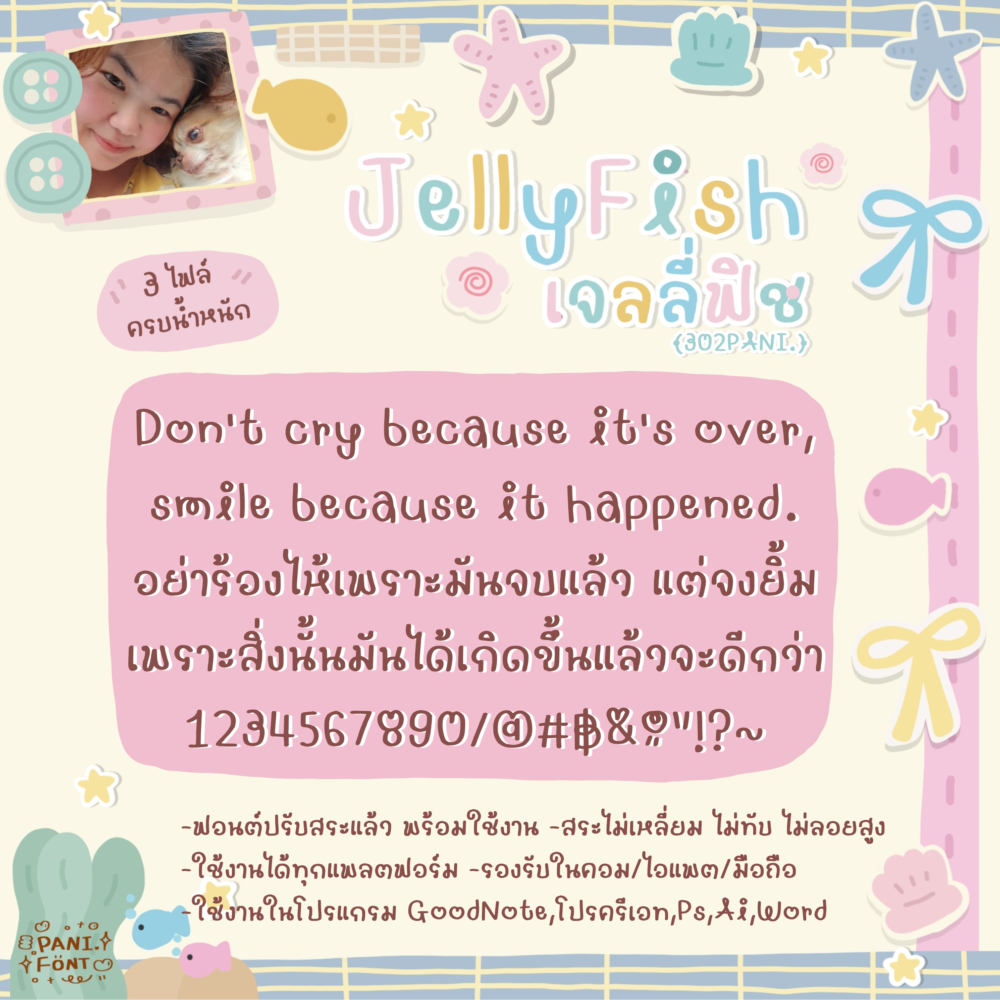
ฟอนต์แมงกะพรุน
นานๆจะเขียนแนวแฟนซีสักที จริงๆชอบเขียนแนวๆนี้มากเลยค่ะ แต่ถึงจะแฟนซีฟอนต์ยังคงอ่านง่ายมากๆอยู่ค่ะ
ตัวฟอนต์สดใส น่ารัก มีความอ้วนๆมลๆดื้อๆทำให้อ่านสนุก
ไม่เบื่อ ใช้งานได้หลากหลาย และยังโดดเด่นในการใช้เป็นหัวข้อด้วย
ฟอนต์มี 3 ไฟล์ - น้ำหนัก บาง ปกติ หนา